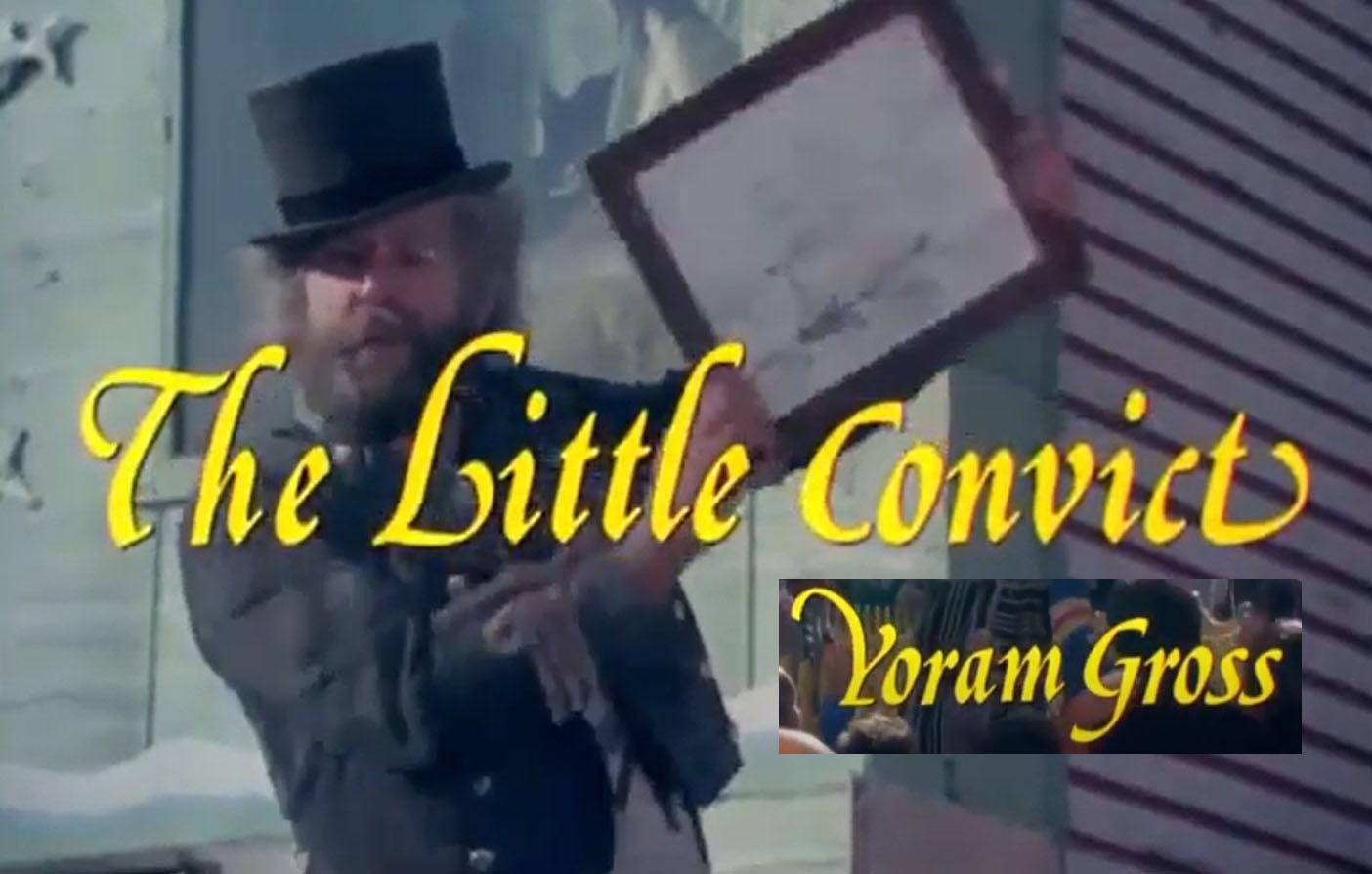
Kursivschrift aus Filmtitel (1979) gesucht
Im Vorspann eines australischen Kinderfilms von 1979 wird eine
mir schon häufiger vorgekommene Kursivschrift verwendet.
Um welche Type handelt es sich wohl?